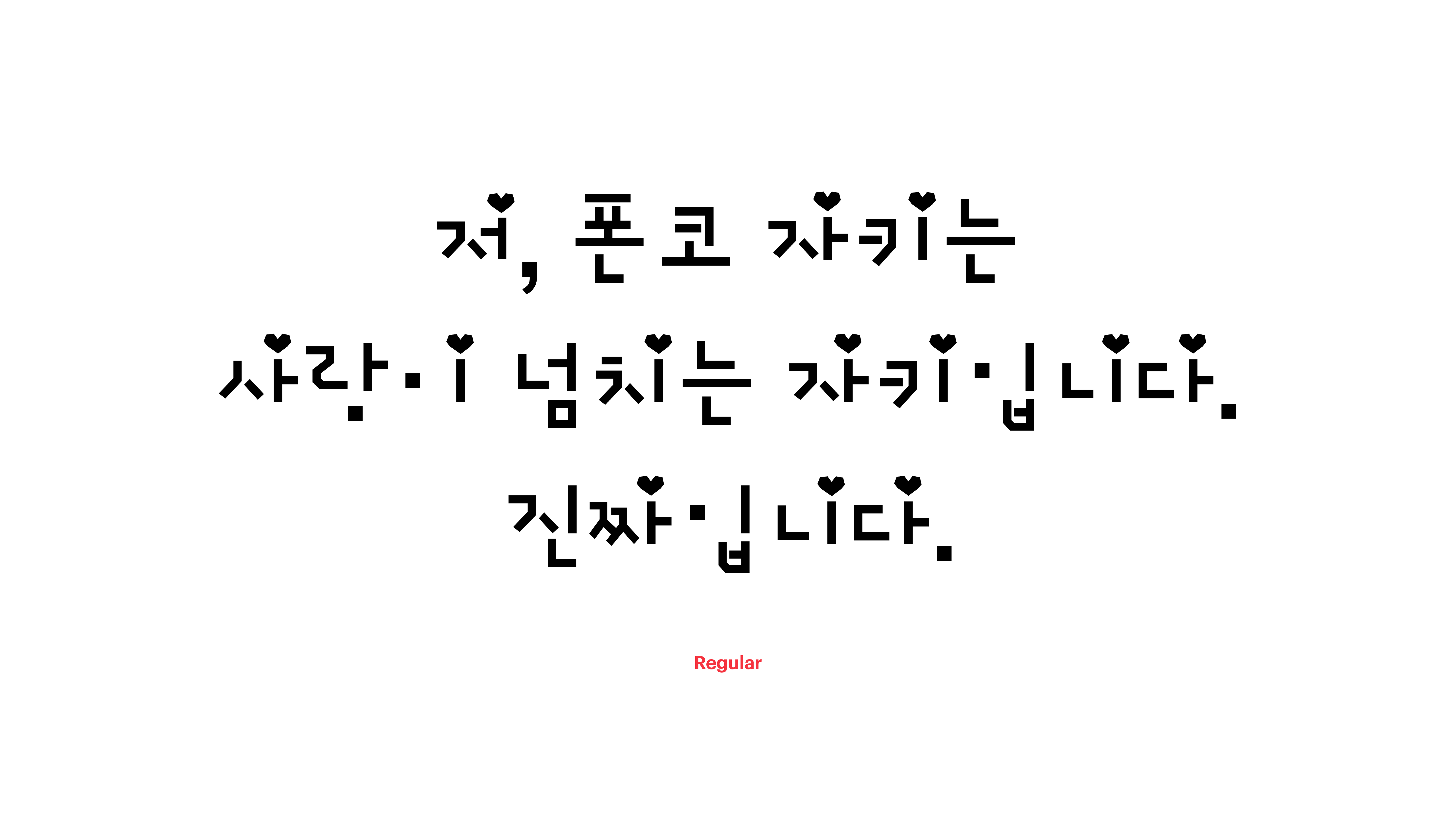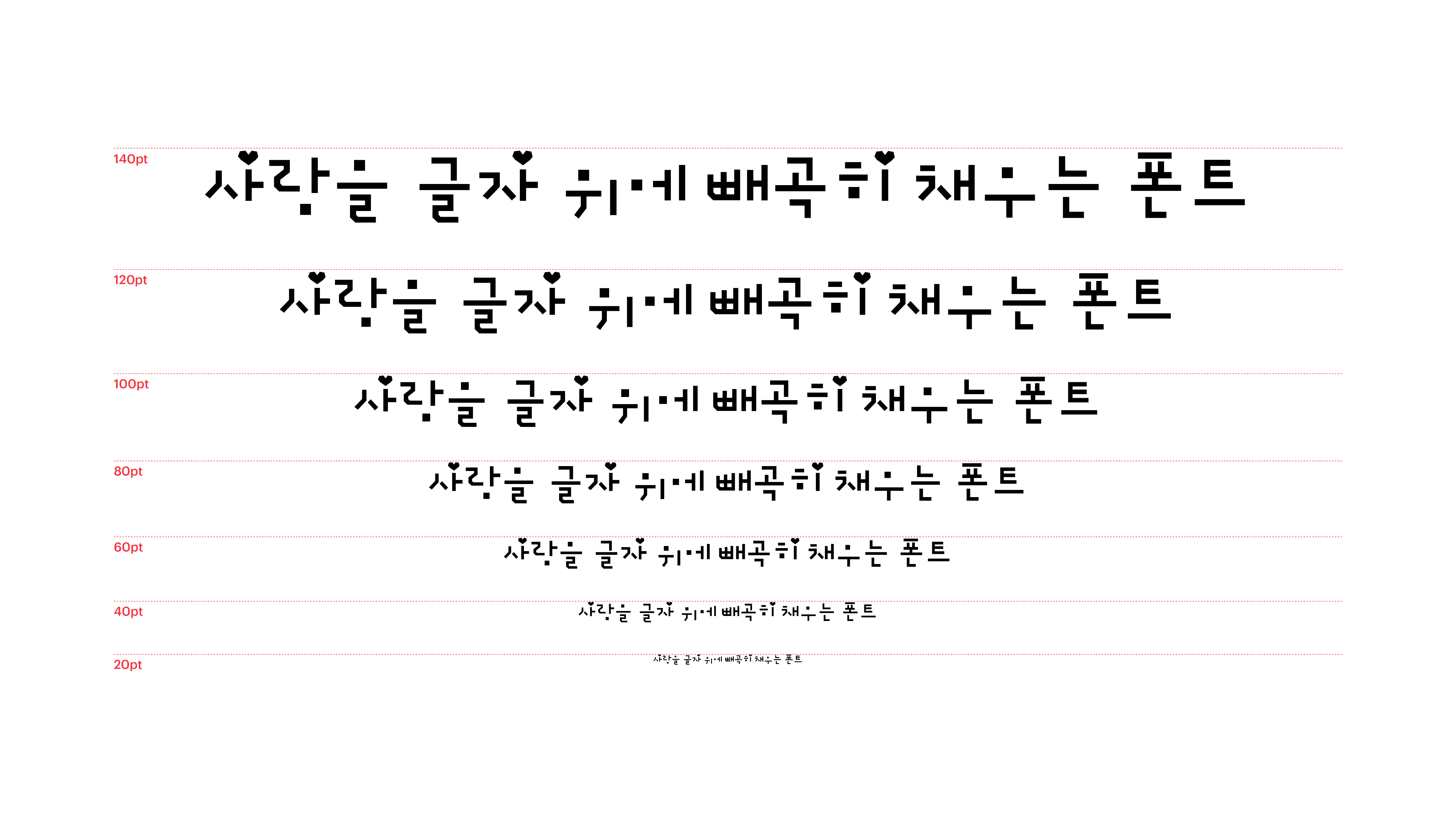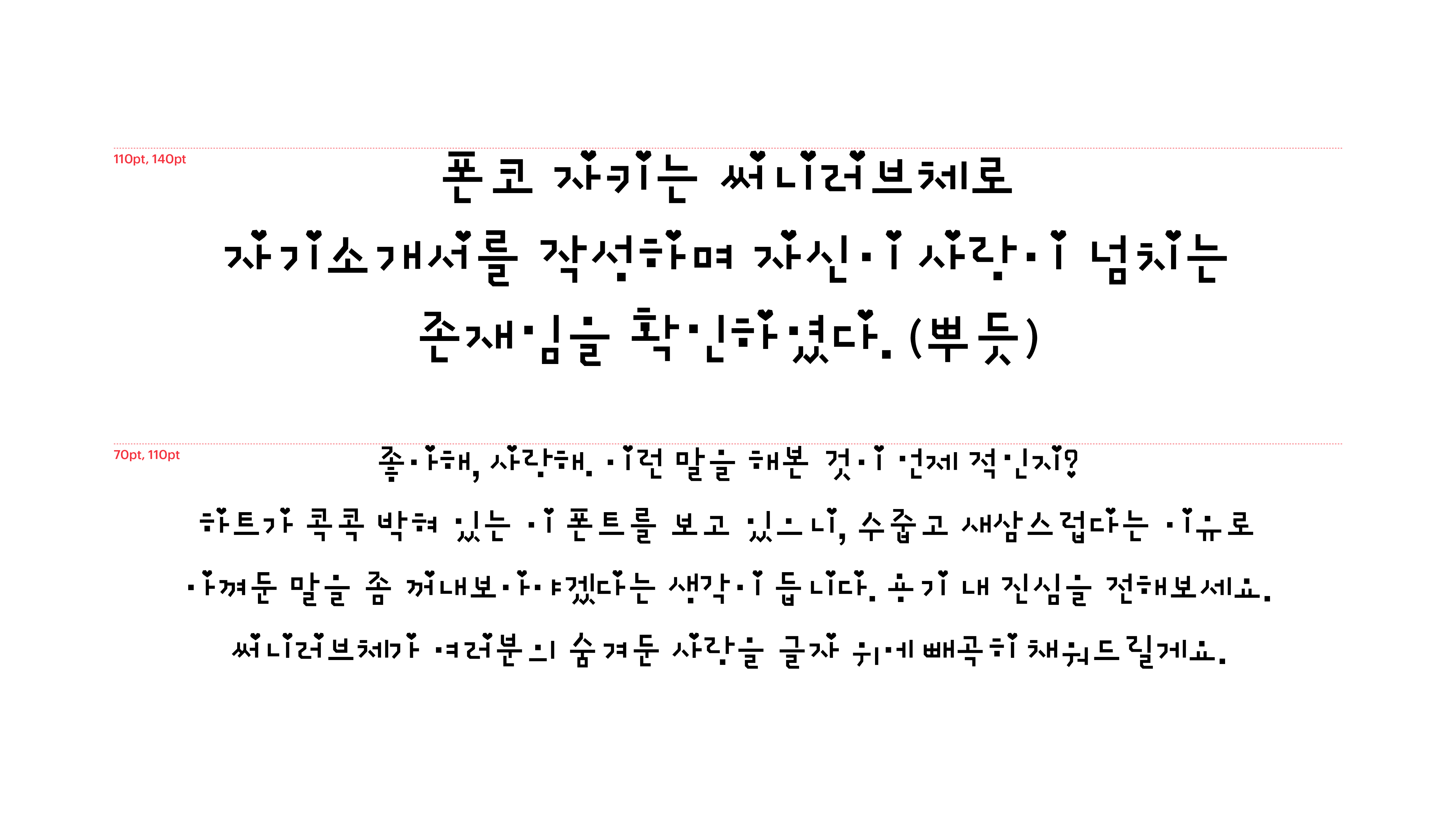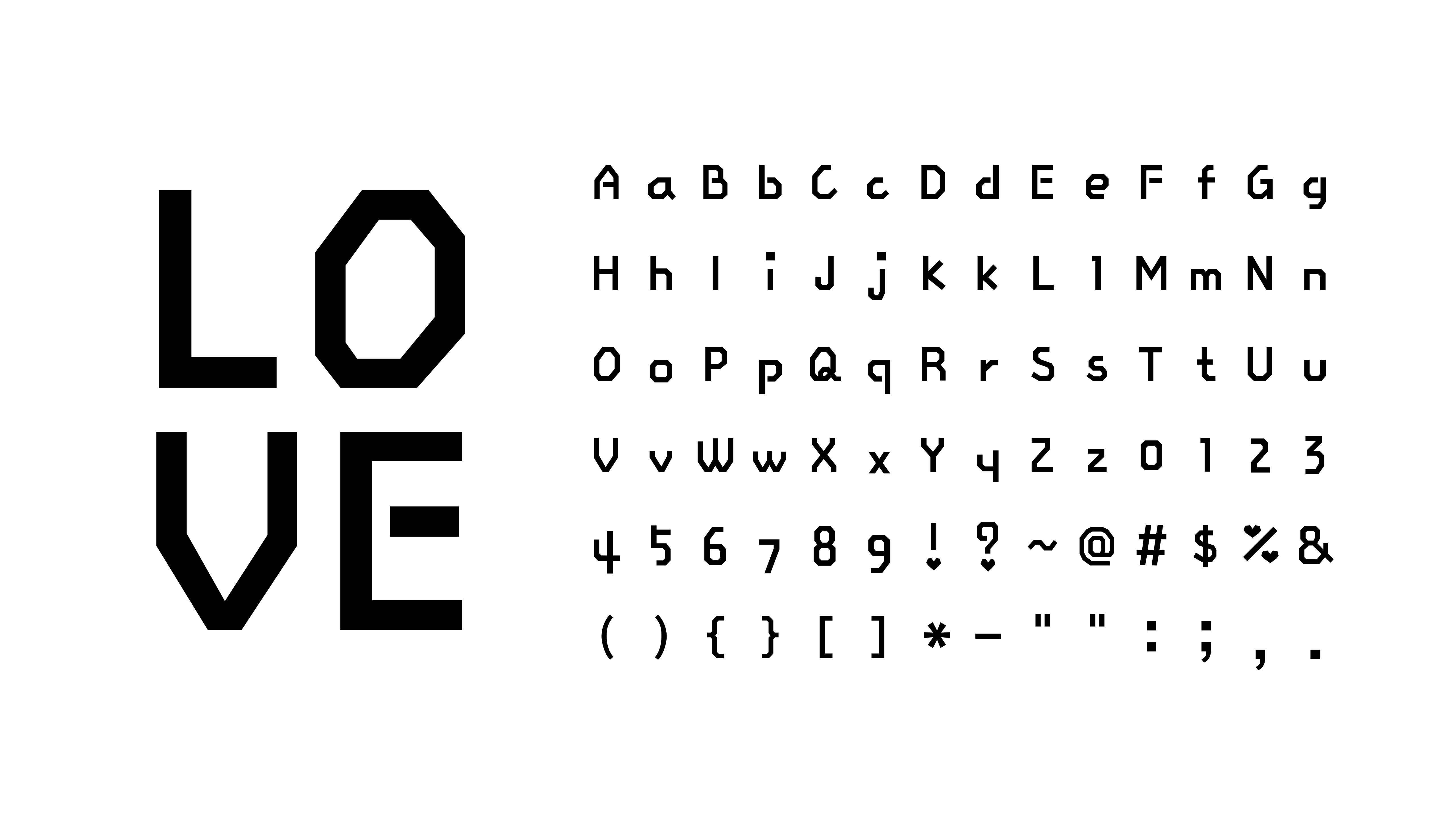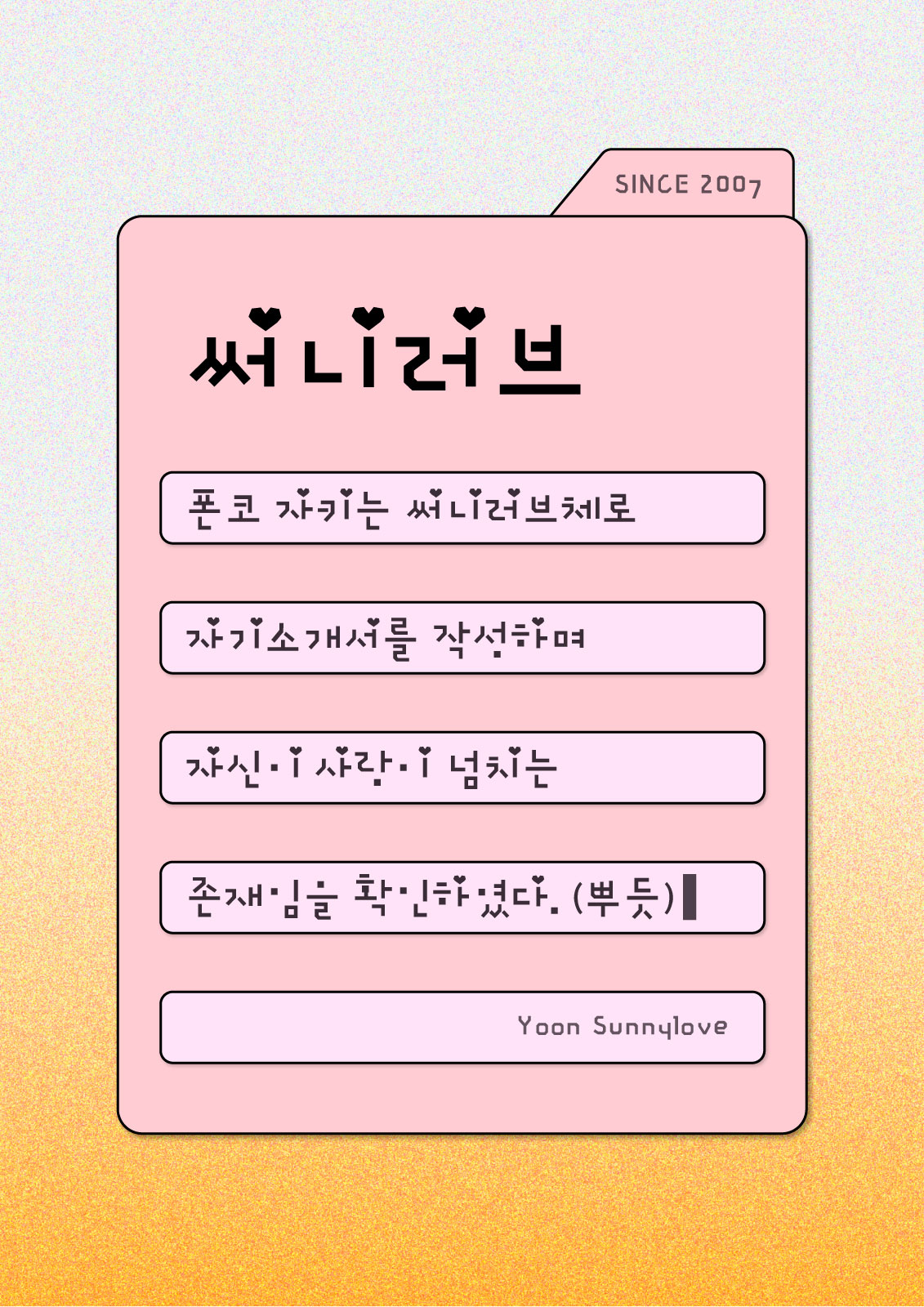
써니러브
Yoon 써니러브
좋아해, 사랑해. 이런 말을 해 본 것이 언제 적인지? 하트가 콕콕 박혀 있는 이 폰트를 보고 있으니, 수줍고 새삼스럽다는 이유로 아껴둔 말을 좀 꺼내보아야겠다는 생각이 듭니다. 용기 내 진심을 전해보세요. 써니러브체가 여러분의 숨겨둔 사랑을 글자 위에 빼곡히 채워드릴게요.